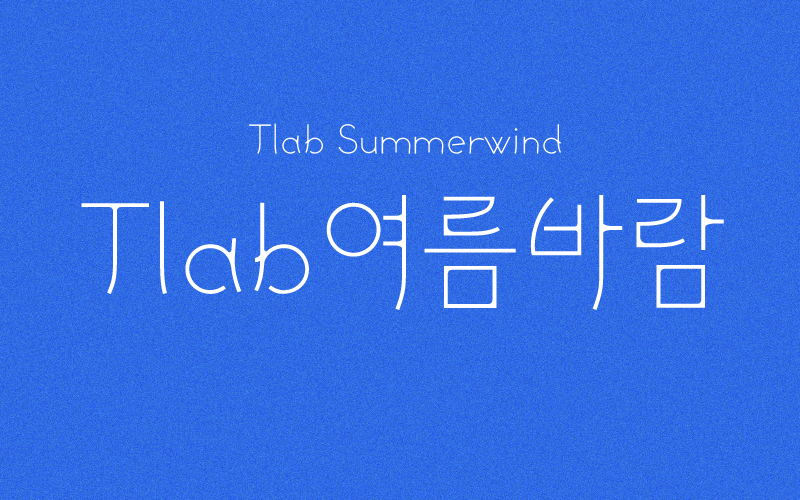
Tlab여름바람
1 종 - Regular불어오는 바람이 여느 때보다 시원하게 느껴지는 여름, 때로는 무더위에 익을 듯한 열기가 솟아납니다. 그 속에서 마주침조차 행복으로 느껴질 한 줄기의 바람. 약하고 짧은 찰나이지만 분명히 존재하는 여름 바람처럼, 얇은 두께감과 곡선 획을 사용하여 자소를 디자인하였습니다.